CSS 웹 안전 폰트란 무엇인가?
웹 안전 글꼴은 모든 브라우저 및 장치에 보편적으로 설치되는 글꼴이다.
CSS fallback 폰트
그러나 100% 완전한 웹 안전 글꼴은 없다. 글꼴을 찾을 수 없거나 올바르게 설치되지 않은 경우가 항상 있다.
따라서 항상 폴백 글꼴을 사용하는 것이 매우 중요하다.
즉, 글꼴 패밀리 속성에 유사한 "백업 글꼴" 목록을 추가해야 한다. 첫 번째 글꼴이 작동하지 않으면 브라우저는 다음 글꼴과 다음 글꼴을 시도한다. 항상 일반 글꼴 패밀리 이름으로 목록을 끝낸다.
여기에는 세 가지 글꼴 유형이 있다: Tahome, Verdana, Sans-serif 두 번째와 세 번째 글꼴은 첫 번째 글꼴을 찾을 수 없는 경우를 대비하여 백업이다.
p요소에 font-family로 폰트를 설정하는데 Tahoma, Verdana, sans-serif 폰트를 설정하였다. 브라우저에서 Tahoma 폰트를 지원하지 않으면 Verdana, Verdana를 지원하지 않으면 sans-serift 폰트를 설정할 것이다.
아래 그림은 위의 코드를 실행한 결과 화면이다.
HTML과 CSS의 최고 웹 안전 폰트
다음 목록은 HTML 및 CSS에 가장 적합한 웹 안전 글꼴이다:
- Arial (sans-serif)
- Verdana (sans-serif)
- Tahoma (sans-serif)
- Trebuchet MS (sans-serif)
- Times New Roman (serif)
- Georgia (serif)
- Garamond (serif)
- Courier New (monospace)
- Brush Script MT (cursive)
CSS Arial 폰트
Arial은 온라인 및 인쇄 매체 모두에 가장 널리 사용되는 글꼴이다. 평가판은 Google 문서의 기본 글꼴이기도 하다.
평가판은 가장 안전한 웹 글꼴 중 하나이며 모든 주요 운영 체제에서 사용할 수 있다.
body 요소에 font-family 에 arial 그리고 sans-serif 폰트를 지정하였다. h1 요소와 p요소에 arial 폰트가 적용된 결과 화면은 아래 그림과 같다.
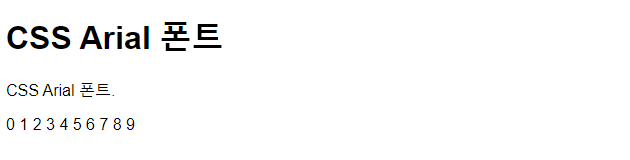
CSS Verdana 폰트
verdana는 매우 인기 있는 글꼴이다. Verdana는 작은 글꼴 크기에서도 쉽게 읽을 수 있다.
body 요소에 font-family 에 verdana그리고 sans-serif 폰트를 지정하였다. h1 요소와 p요소에 verdana 폰트가 적용된 결과 화면은 아래 그림과 같다.
CSS Tahoma 폰트
Tahoma 글꼴은 문자 사이의 공간이 적다.
body 요소에 font-family 에 tahoma 그리고 sans-serif 폰트를 지정하였다. h1 요소와 p요소에 tahoma 폰트가 적용된 결과 화면은 아래 그림과 같다.
CSS Trebuchet MS 폰트(sans-serif)
Trebuchet MS는 1996년에 마이크로소프트에 의해 설계되었다. 이 글꼴을 주의해서 사용하해야 한다. 일부 모바일 운영 체제에서는 지원되지 않는다.
body 요소에 font-family 에 'Trebuchet MS' 그리고 sans-serif 폰트를 지정하였다. h1 요소와 p요소에 'Trebuchet MS' 폰트가 적용된 결과 화면은 아래 그림과 같다.
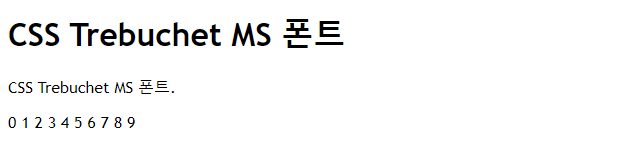
CSS Times New Roman 폰트(serif)
Times New Roman은 세계에서 가장 인지도가 높은 글꼴 중 하나이다. 그것은 전문적으로 보이고 많은 신문과 "뉴스" 웹사이트에서 사용된다. Windows 장치 및 응용 프로그램의 기본 글꼴이기도 하다.
body 요소에 font-family 에 'Times New Roman' 그리고 sans-serif 폰트를 지정하였다. h1 요소와 p요소에 'Times New Roman' 폰트가 적용된 결과 화면은 아래 그림과 같다.
CSS Georgia 폰트(serif)
Georgia는 우아한 세리프 글꼴이다. 다양한 글꼴 크기에서 매우 읽기 쉬우므로 모바일 응답 설계에 적합하다.
body 요소에 font-family 에Georgia 그리고 sans-serif 폰트를 지정하였다. h1 요소와 p요소에Georgia 폰트가 적용된 결과 화면은 아래 그림과 같다.
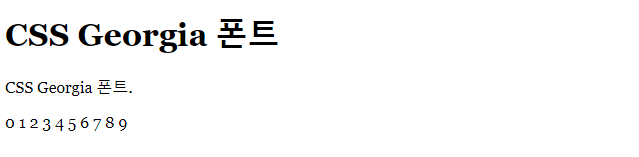
CSS Garamond 폰트(serif)
Garamond 는 많은 인쇄된 책에 사용되는 고전적인 글꼴이다. 그것은 시대에 뒤지지 않는 모습과 좋은 가독성을 가지고 있다.
body 요소에 font-family 에 Garamond 그리고 sans-serif 폰트를 지정하였다. h1 요소와 p요소에 Garamond 폰트가 적용된 결과 화면은 아래 그림과 같다.
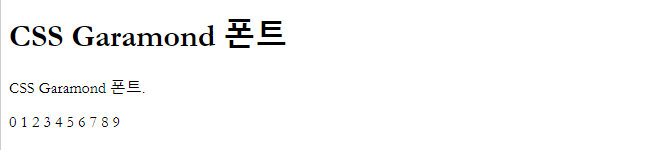
CSS Courier New 폰트(monospace)
Courier New는 가장 널리 사용되는 단일 공간 세리프 글꼴이다. Courier New는 코딩 디스플레이와 함께 사용되는 경우가 많으며 많은 전자 메일 공급자가 기본 글꼴로 사용한다. Courier New는 영화 스크린플레이의 표준 글꼴이기도 하다.
body 요소에 font-family 에 'Courier New' 그리고 sans-serif 폰트를 지정하였다. h1 요소와 p요소에 'Courier New' 폰트가 적용된 결과 화면은 아래 그림과 같다.
CSS Brush Script MT 폰트
Brush Script MT 글꼴은 필기를 모방하도록 설계되었다. 그것은 우아하고 세련되었지만 읽기 어려울 수 있다. 조심해서 사용하세요.
body 요소에 font-family 에 'Brush Script MT' 그리고 sans-serif 폰트를 지정하였다. h1 요소와 p요소에 'Brush Script MT' 폰트가 적용된 결과 화면은 아래 그림과 같다.
지금까지 CSS 폰트에서 웹 안전 폰트에 대해서 살펴보았다.
CSS 웹 안전 폰트에는 ,Arial, Verdana, Tahoma, 'Trebuchet MS', 'Times New Roman', Georgia, Garamond, 'Courier New', 'Brush Script MT' 폰트에 대해서 살펴보았다.